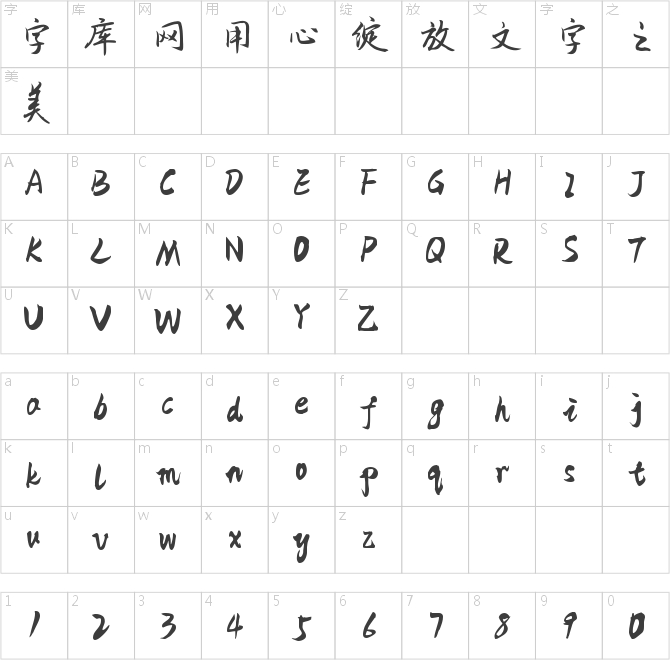
字體名稱: 千圖筆鋒手寫體
千圖筆鋒手寫體
千圖筆鋒手寫體介紹
【千圖筆鋒手寫體】定義為一款清新的創意手寫字體。在字形筆畫上改變了平直的筆畫,用柔和的弧線將字體的柔美發揮的淋漓盡致,字形新穎獨特,簡潔有力,清新淡雅,文藝范十足。整體采用連筆寫法,一氣呵成,更顯流暢。適用于海報 、影視綜藝、文藝宣傳等場景。